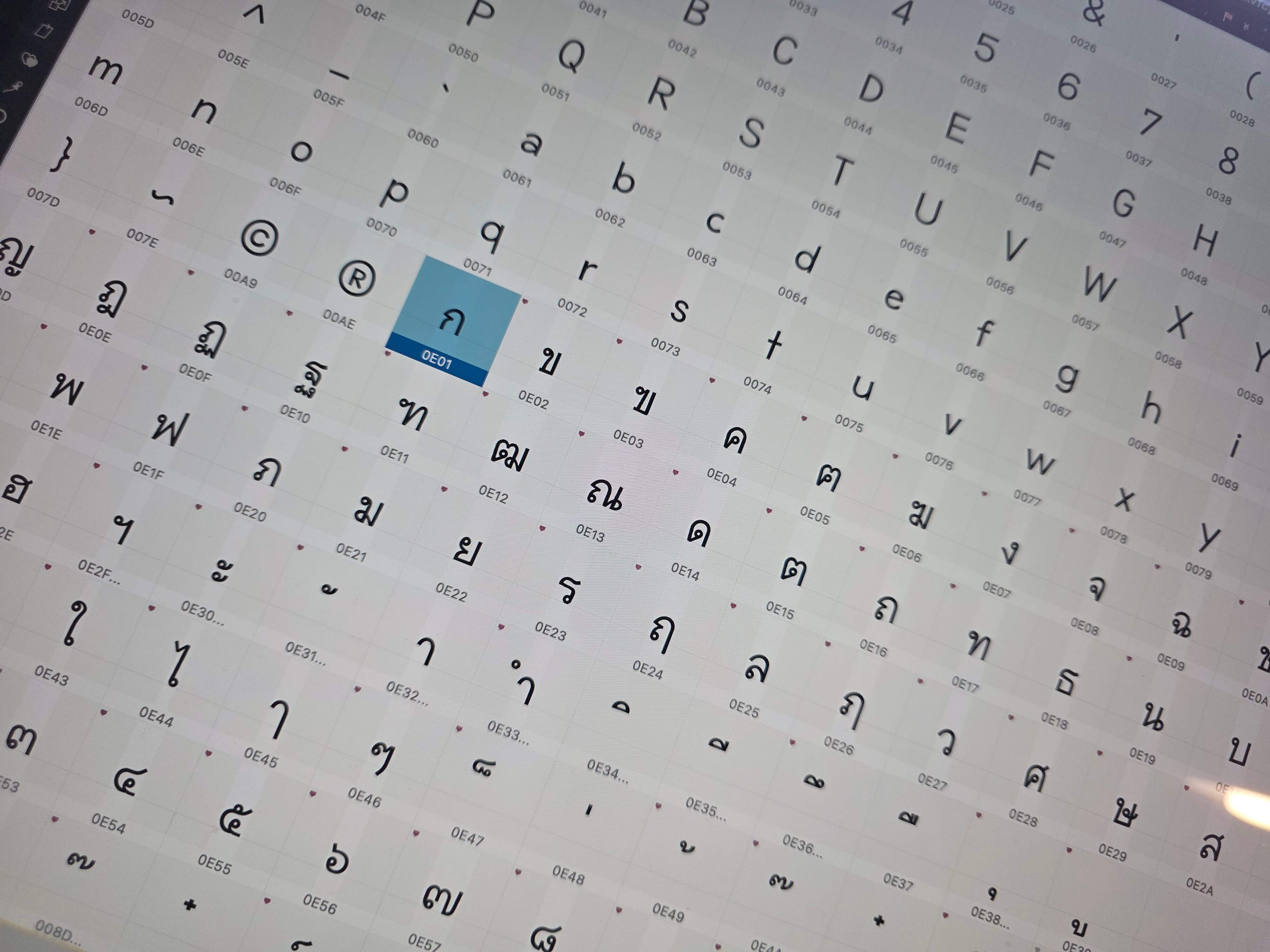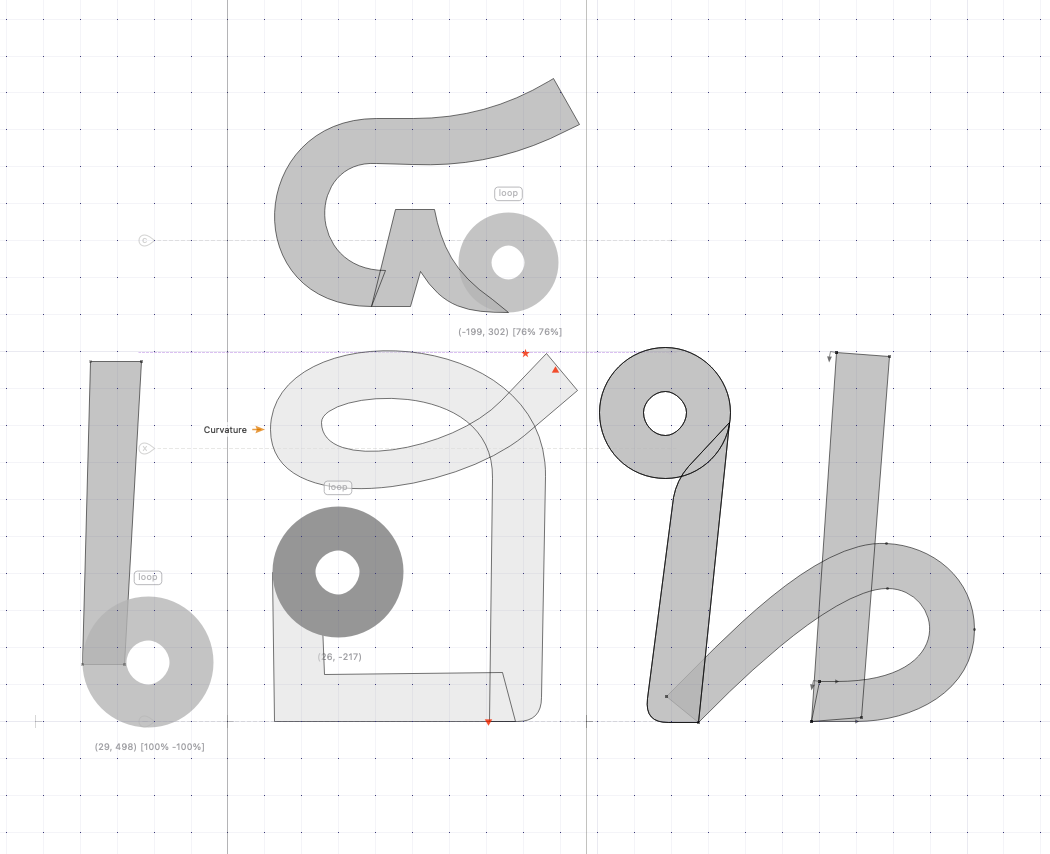
ฟอนต์แม่ไก่ (iannnnn-HEN)
หลังจากปล่อยฟอนต์หมา แล้วได้รับเสียงตอบรับที่ดีเกินคาด
ก็เลยบ้าเห่อครับ :49:
อยากทำฟอนต์ใหม่ขึ้นมาในขณะที่กำลังใจเต็มเปี่ยม
ทีนี้ตอนออกแบบฟอนต์หมาเนี่ย โจทย์คืออยากให้เป็นฟอนต์ลายมือแบบที่ตัวเองอยากได้ อยากใช้งานแบบจริงจัง
ต่างจากฟอนต์เป็ดที่แรงผลักดันคืออยากกลับมาหัดทำอีกครั้งในรอบสิบกว่าปี
พอออกมา มานั่งดูก็เป็นฟอนต์ที่ตัวเองคงยังไม่ค่อยได้หยิบไปใช้นัก (อย่าร้องนะเป็ดน้อย :25:)
ตอนนี้ตัวที่สามในศตวรรษนี้ โจทย์คืออยากลองทำฟอนต์ที่เป็นการดัดเส้นสักหน่อยครับ
ที่ผ่านมา 2 ตัว เป็นฟอนต์ลายมือตัวเอง ทำสนองนี้ดตัวเองเป็นหลัก
อย่างตัวใหม่นี่อยากให้เป็นฟอนต์ "ไม่ลายมือ" แต่ก็ยังมีกลิ่นเดิมอยู่
คือฟอนต์ที่ทำได้เร็ว ง่าย เหมาะกับคนที่สมาธิมีจำกัดอย่างผม :59:
ก็เลยเป็นฟอนต์ที่จะไม่เนี้ยบ เหมือนเดิม เพียงแต่เปลี่ยนจากการขึ้นรูปด้วยปากกา ผ่านไอแพด เอามา trace
ให้กลายเป็นฟอนต์ที่ขึ้นรูปด้วยเส้นตรง เส้นโค้ง แต่ยังมีความเป็นมิตร ขี้เล่นเหมือนเดิม
ในหัวคิดไปถึงการรื้อ iannnnnGMO ที่เคยทำไว้หลายปีก่อน
ที่จนถึงตอนนี้ก็ยังมีคนใช้งานฟอนต์นี้อยู่เยอะมากเลย มีคนชอบมันมากๆ ด้วย
แต่จากสายตาคนทำที่แก่ตัวลงจากปี 2006 พอสมควร ผมว่าปัญหาในฟอนต์นั้นมันเยอะมาก :16:
มีแต่ความไม่สมบูรณ์เต็มไปหมด :16: บางทีอยากลบฟอนต์เดิมทิ้ง แต่เสียดาย
เพราะมันคือส่วนหนึ่งของยุคสมัยที่เราโตมากับมัน และทำให้เด็กนักเรียนเอาไปทำรายงานโดนครูด่ามานักต่อนัก :30:
ขอเล่าความรู้สึกไว้อย่างซื่อตรงแบบนี้แหละนะครับ
จะได้เป็นบันทึกแรงบันดาลใจในการสร้างฟอนต์ตัวใหม่จ้ะ
อะ ทีนี้โจทย์คือจะหาทางรื้อฟอนต์ iannnnnGMO เป็นเวอร์ชันใหม่ที่มันเป็น 2021 มากขึ้น
ภาพในหัวที่ออกมาชัดเป็นตัวแรกคือ ก.ไก่ ครับ
ก.ไก่ที่อยากให้เป็น มันวนอยู่ในหัวแบบนี้มาหลายปี เลยเริ่มจากตัวนี้
แล้วงอกไปตัวอื่น เรื่อยๆ
เอกบักษณ์คือ ภาษาไทยทั้งชุดจะมีหัวกลมโต และเส้นตรง เส้นโค้ง ที่บิดไปบิดมาแค่นิดหน่อย
แต่เอามาจัดวางลงใน "หนังสือเด็ก" (นี่ วางโจทย์ไว้ก่อนว่าให้เอาไปใช้ในนี้) ได้พอดี
ส่วนอื่นๆ ยังค่อยๆ เกลาต่อไปครับ ไม่รีบ ฟอนต์นี้คิดว่าอีก 2 เดือนแหละคงเสร็จ
แล้วจะมาอัปเดตเป็นระยะๆ ครับ
GMO ผมก็ชอบใช้นะ  เวลาจะเขียนอะไรที่กึ่งทางการ
ตัวใหม่นี้ โดน ตั้งแต่ ก.ไก่ เลย  พอเห็นน้ำหนักแล้ว .... ตัว donate อาจเป็น 9 น้ำหนัก หรือ variable font ได้เลย  (จริงๆ น่าจะลองดูระบบ Multi Master เพื่อช่วยให้งานง่ายขึ้น)
หมายเหตุ  ตื่นเต้นจริงแหละ หรือจงใจ CHICKEN กลายเป็น CHICHEN (แม่ไก่ chic ก็ ok นะ)  เอกลักษณ์ กลายเป็น เอกbug (อันนี้โปรแกรมเมอร์กลัว)
รอลุ้นต่อเด้อ
:3005: แก้ๆๆๆๆๆ สะกดเผียดครับ
เรื่อง Variable ก็น่าสนใจ เพราะฟอนต์นี้เริ่มจากโครงเลย
แต่ไม่รู้พลังผมจะถึงหรือเปล่า เดี๋ยวลองหาวิธีดูครับ :46:
งานนี้ผมว่าโรงพิมพ์หนังสือหรืองานกิจกรรมเด็กๆปฐมวัยแนว ก.ไก่-ฮ.นกฮูก คงได้ใช้บริการแล้วล่ะครับ น่ารักดี
ขุดครับ
ด้วยความรู้สึกผิดที่ทิ้งร้างไปข้ามปี (จะปีแล้วจริงๆ)
ตอนนี้ผมกลับมาทำฟอนต์ไก่ต่อละครับ เปลี่ยนชื่อเป็นแม่ไก่ (iannnnn-HEN) ซะเลย  :30:
คือมันยากอ้ะ :30: ไม่ถนัดฟอนต์ที่มันหน้าตามีสัดส่วน ที่ผ่านมาทำแต่มั่วๆ หรือลายมือ
เลยเอามาโพสต์กดดันตัวเองไว้ก่อน ดองมานานเหลือเกิ๊น
ส่วนจะเป็น Variable Font หรือเปล่านั้นเดี๋ยวขอดูอีกทีนะครับ เพราะพอทิ้งไว้นานก็ลืมวิชาหมดอีกแล้ว
ต้องรื้อฟื้นใหม่เลย เดี๋ยวขอผ่านขั้นตอนออกแบบให้เสร็จก่อน
แต่ก็คงเสร็จปีนี้แหละ 5555
อัปเดตความคืบหน้าครับ นั่งทำวันละนิดวันละหน่อย
อยากว่างทำนานๆ จังเลย :3005:
อัปเดต :
ผ่านมา 1 ปี ขอรื้อทำใหม่เลยครับ :3005:
มีโจทย์ในใจที่อยากทำมานานแล้ว แต่ที่เคยทำทั้งฟอนต์ไก่ (เดิม) กับฟอนต์แม่ไก่ (ที่ทิ้งมาปีนึง)
ตอนนี้พลังมาแล้วครับ ก็คงได้เริ่มดำเนินการซะที
เดี๋ยวมีอะไรจะโน้ตๆ ไว้ครับ ในฐานะของเล่น และเผื่อไว้มือใหม่มาอ่านเผื่อจะได้ติดไปบ้างก็คงดีครับ
รอชมครับ  :45: :45: :45:
แปะไว้ก่อนว่าตัวนี้ไม่ได้ฤกษ์เริ่มทำต่อซะที :3005:
เดี๋ยวขอสลับไปทำนกฮูกก่อนนะครับ
พูดไปก็อายครับ แต่ขอบันทึกไว้ละกัน  :05:
ผ่านมา 1 ปีจากคราวก่อนที่หยุดไป รวมๆ แล้วฟอนต์นี้ใช้เวลาหลายปี (แต่ทำจริงๆ แป๊บเดียวนะ 555555)
ตอนนี้อยากทำแล้วครับ แต่ขอรื้อโจทย์ใหม่ เป็นการกลับมาหัดใช้ฟอนต์แล็บอีกครั้ง
แต่คราวนี้เป็นเส้นดัดๆ ตรงๆ เหลี่ยมๆ นี่แหละ แล้วก็ใส่หัวกลมเข้าไป
ทำให้มันโย้เย้ๆ นิดนึง เพราะจะสานต่อจาก iannnnnGMO ในอดีต
ที่ทำขึ้นมาล้อเลียนฟอนต์มาตรฐานๆ แต่ทำให้มันเบี้ยวๆ หนุกดี
เพียงแต่มาดูตอนนี้แล้วมันเศร้าๆ (เหมือนคนออกแบบทั่วไปที่มองงานตัวเองในอดีตแล้วอยากกลับไปลบทิ้ง)
ตัวนี้เลยทำแบบไม่โฉ่งฉ่างมาก ไม่ตะโกนบุคลิกออกมามากนัก
แต่ก็ยังพอดูออกว่าเหมือนฟอนต์ที่ชินตาในสมัยก่อน เอามาปรับให้มันดูเล่นๆ มากขึ้น
น่าจะได้ใช้งานเป็นปัจจุบันมากขึ้นจ้ะ
ชอบหางไก่ของหนู
คนอื่นเขาทำฟอนต์กัน 4 วัน ของเรา 4 ปียังไม่เสร็จ :3005:
เพิ่งทำตัวอักษรครบ เหลือ
- ช่องไฟ, kerning
- marking ต่างๆ (คราวนี้จะลองหัดแยกวรรณยุกต์ทุกตัวดู ไม่รวมเป็นก้อนเดียว)
- ลองเพิ่มน้ำหนักดู
- แล้วก็ตรวจวนๆๆๆๆ
เดือนนี้ต้องเสร็จให้ได้  :59: